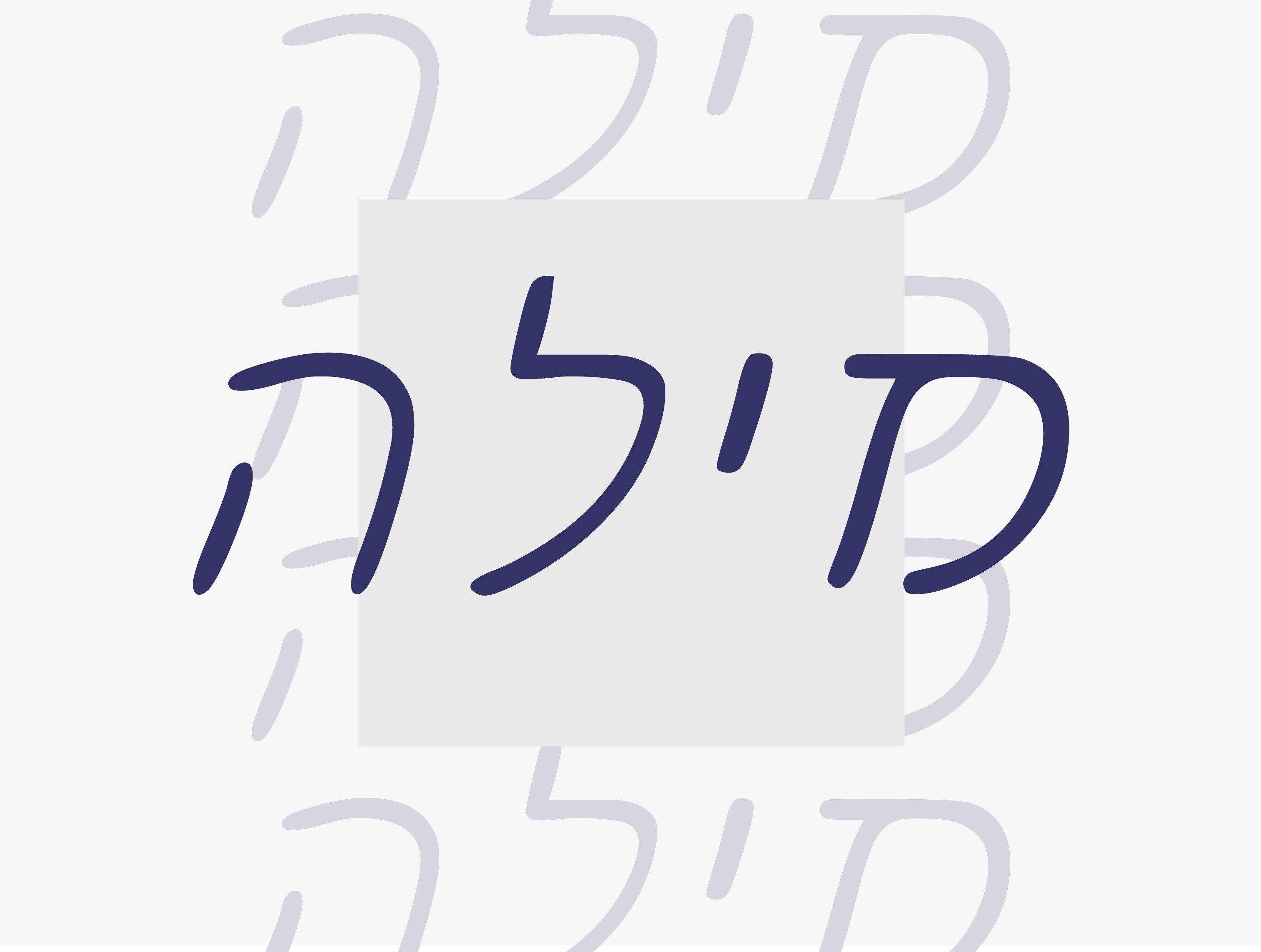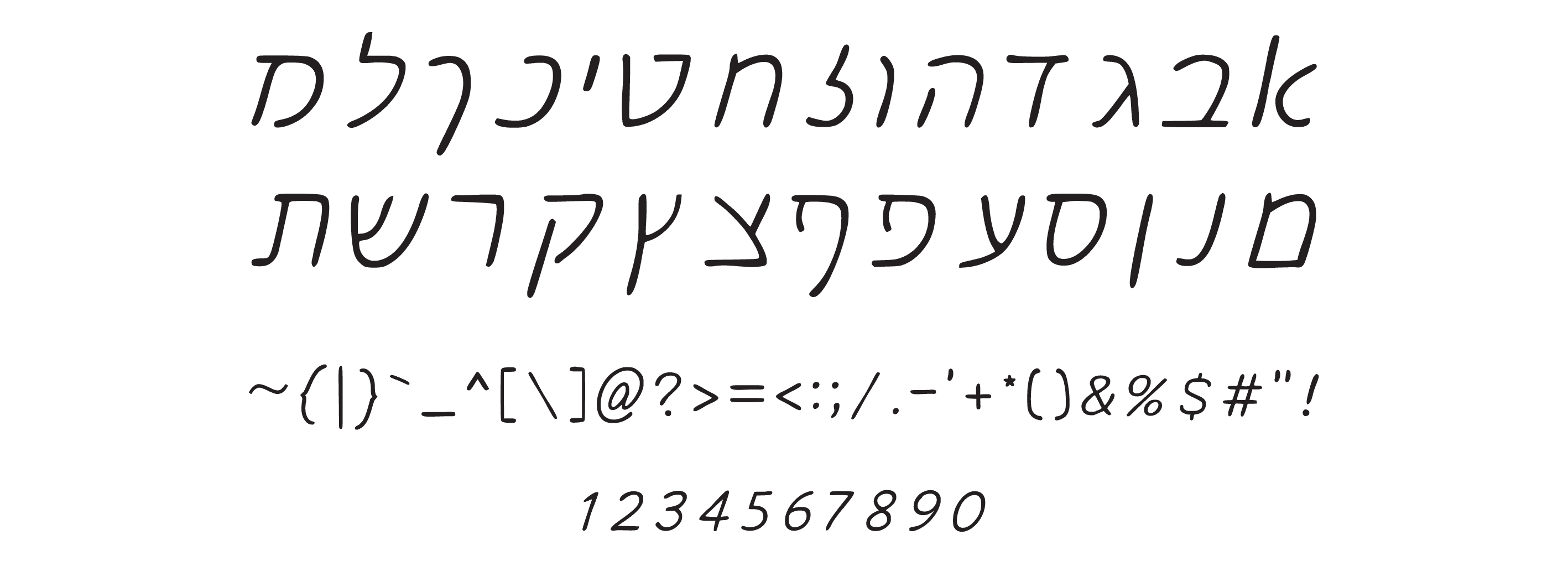
פונט מילה
פונט עברי קליל, אישי ונעים, בסגנון כתב יד רך ומזמין.
מילה — פונט שמדבר בגובה העיניים
לא כל טקסט צריך להיות כבד או דרמטי.
מילה הוא פונט עברי רך, נעים ואנושי, שזורם כמו שיחה בין חברים.
הוא נוצר מתוך אהבה לכתב יד פשוט, עם קווים עגולים ונקיים, ונותן לכל עיצוב תחושה חמה, פתוחה ואישית.
מתאים בדיוק לרגעים שבהם את/ה רוצה שהמילים ירגישו קרובות, קלות לקריאה ומלאות בנשמה.
איפה הוא מרגיש בבית?
✦ ברכות והזמנות
✦ בלוגים ופוסטים אישיים
✦ עיצובי ניירת רכה
✦ מיתוג אישי חמים ונעים
למי הוא מתאים?
לכל מי שמחפש פונט עברי בגובה העיניים — נעים, קריא ומלא חום אנושי.